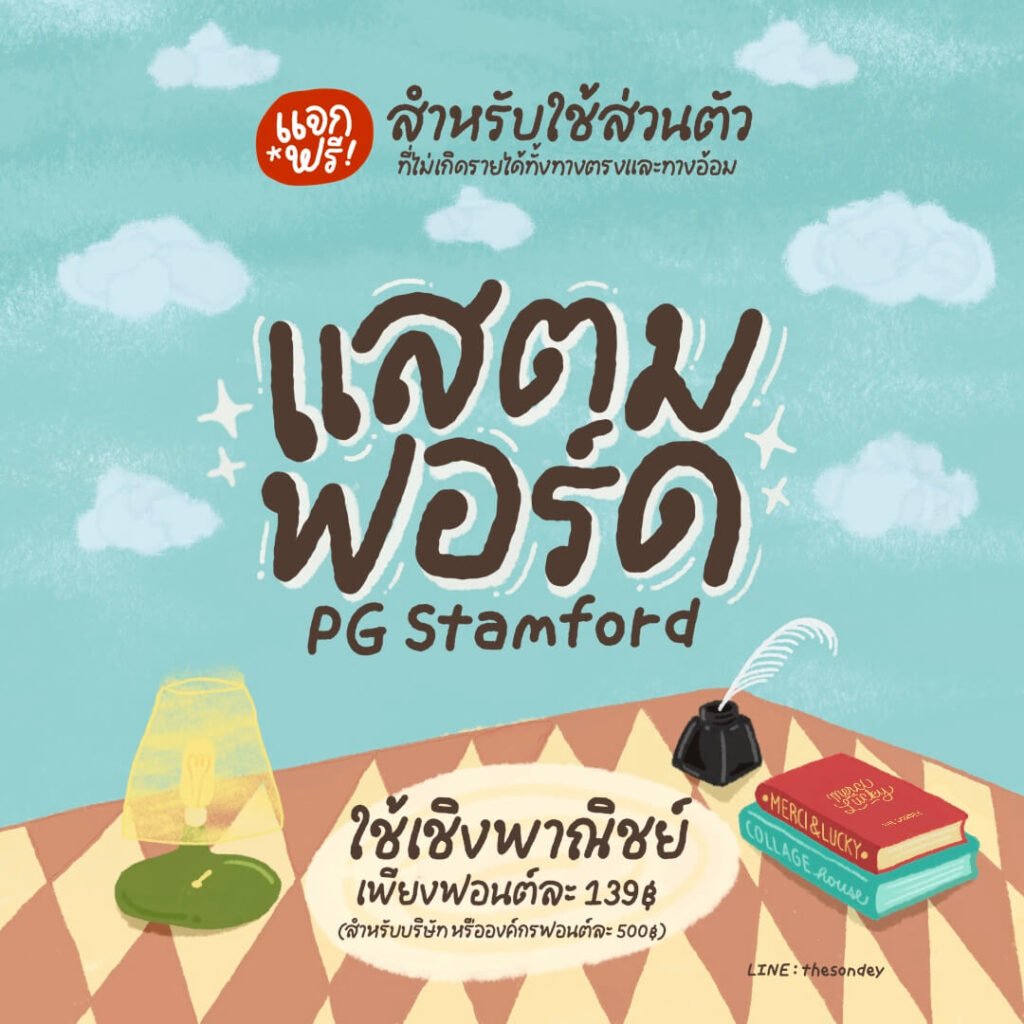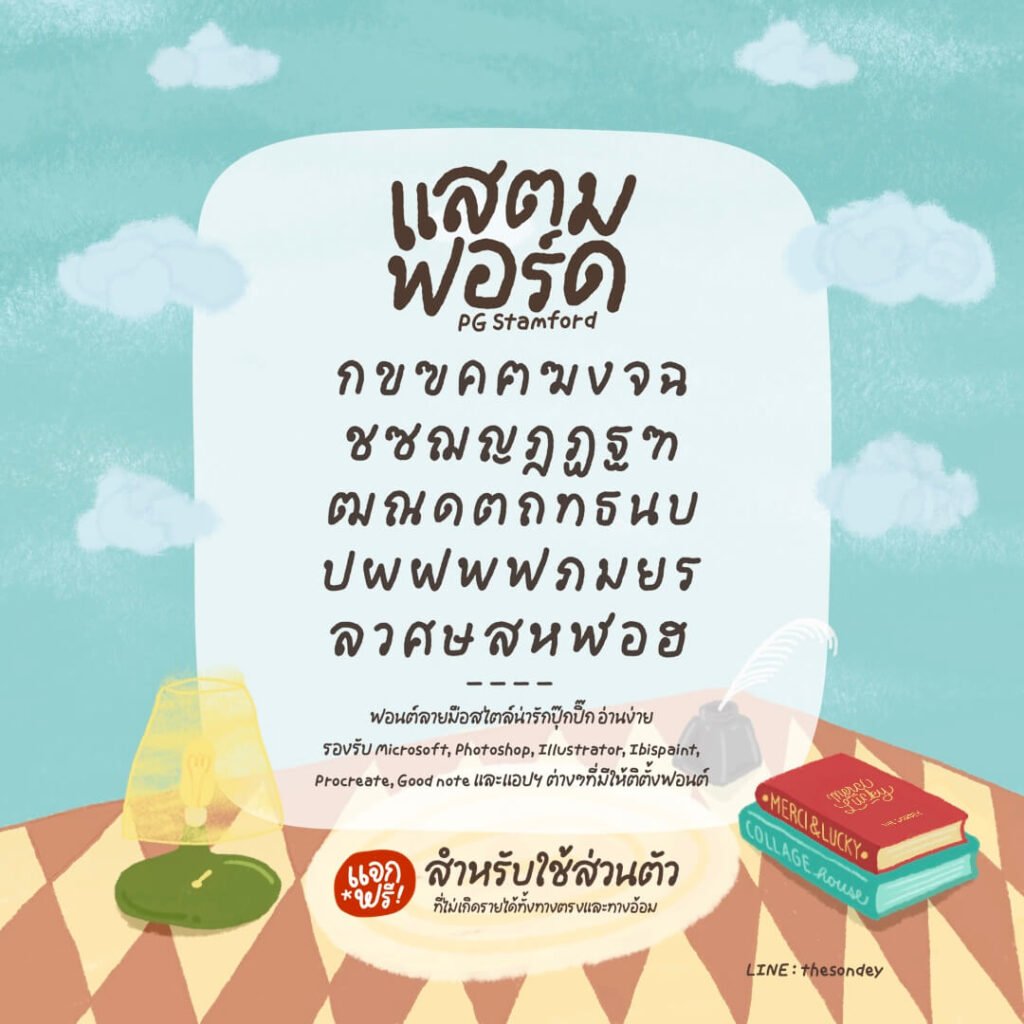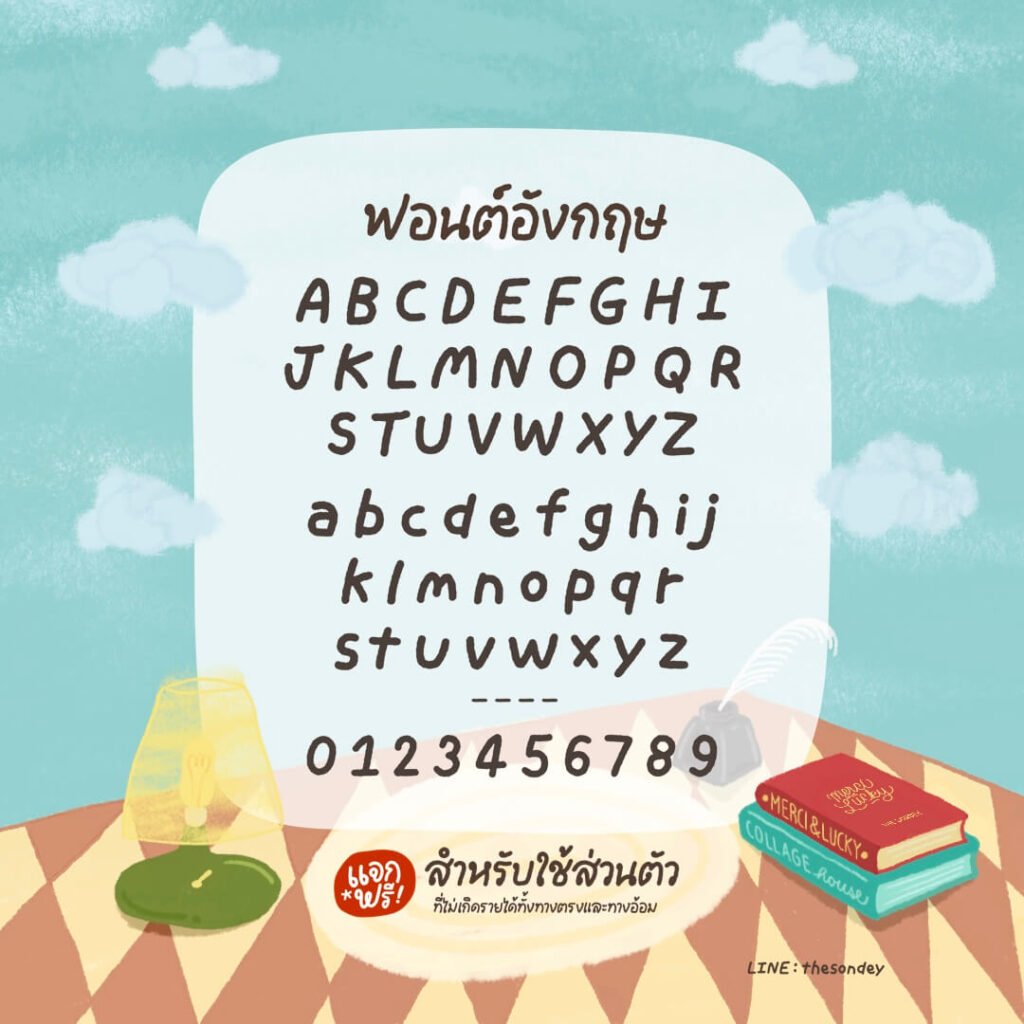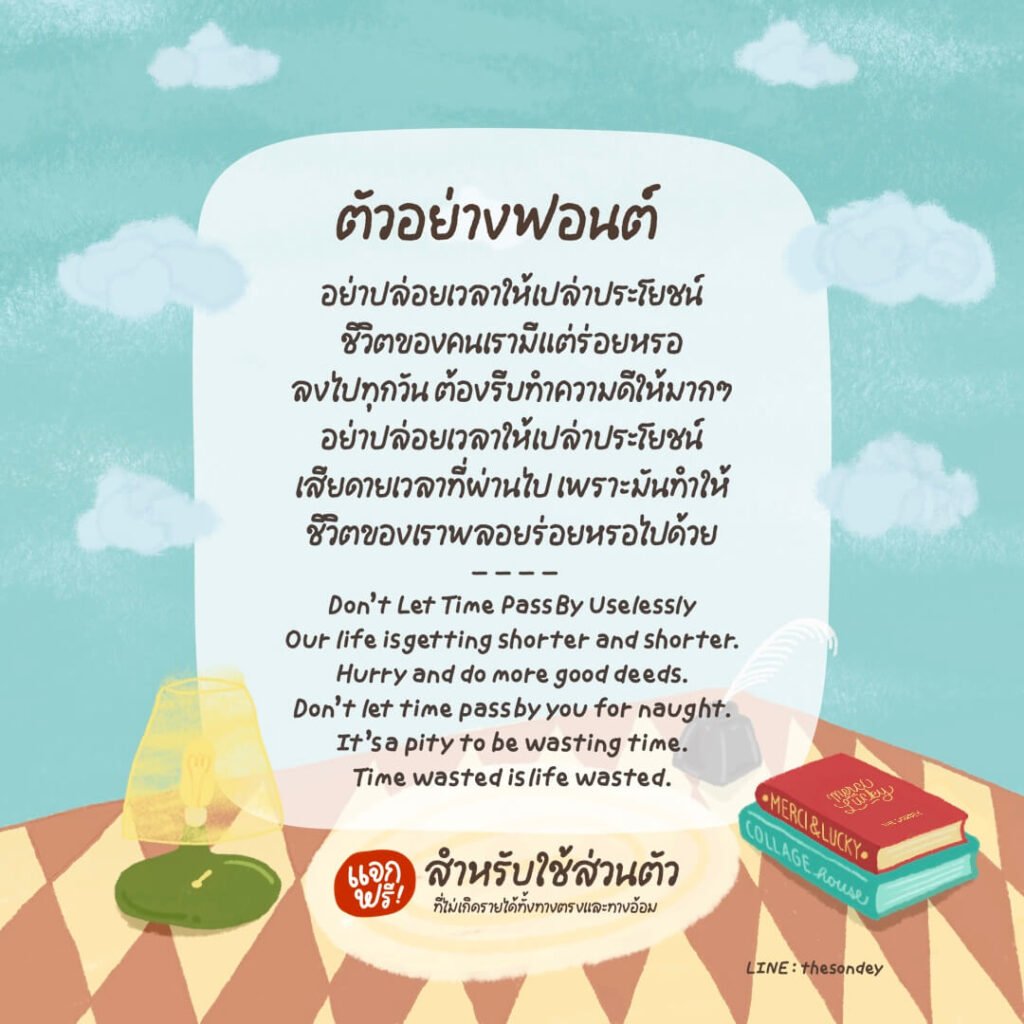
แสตมฟอร์ด (PG Stamford)
ฟอนต์ลายมือสไตล์น่ารักปุ๊กปิ๊ก อ่านง่าย รองรับ Microsoft, Photoshop, Illustrator, CapCut, ibisPaint, Procreate, Good Note และแอปฯ ต่างๆ ที่มีให้ติดตั้งฟอนต์